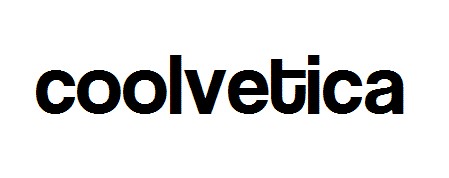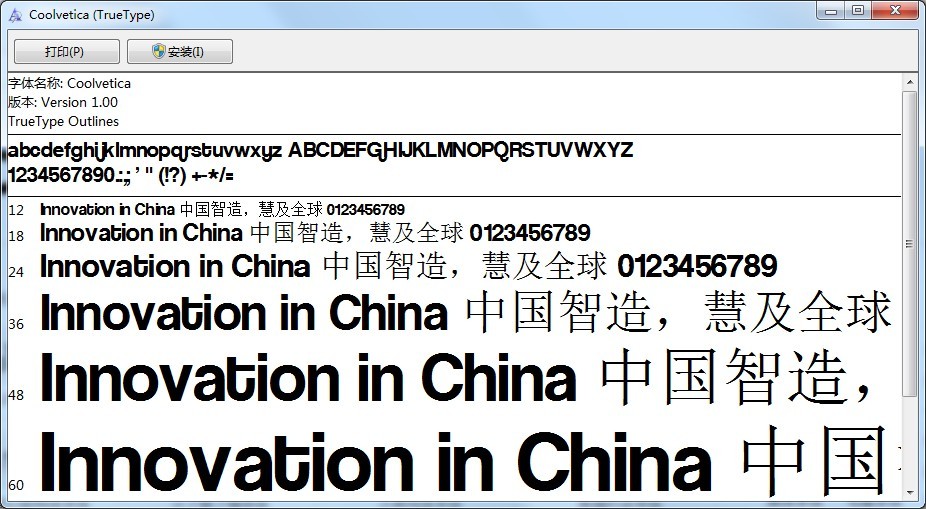
coolvetica font適用于各類(lèi)場(chǎng)景當(dāng)中ttf格式的英文字體,端莊的正版字體效果可以讓?xiě)?yīng)用在正式書(shū)面或是各類(lèi)設(shè)計(jì)內(nèi)容當(dāng)中,此字體主要是轉(zhuǎn)換英文字體,中文字體保持原有不變,有需要的用戶可以來(lái)下載了解更多。
coolvetica是非常漂亮的英文字體,字體設(shè)計(jì)優(yōu)美、秀麗大方,書(shū)寫(xiě)流暢,整體效果非常漂亮,適合應(yīng)用于海報(bào)設(shè)計(jì)、書(shū)籍裝幀、畫(huà)冊(cè)封面、產(chǎn)品包裝設(shè)計(jì)等應(yīng)用。